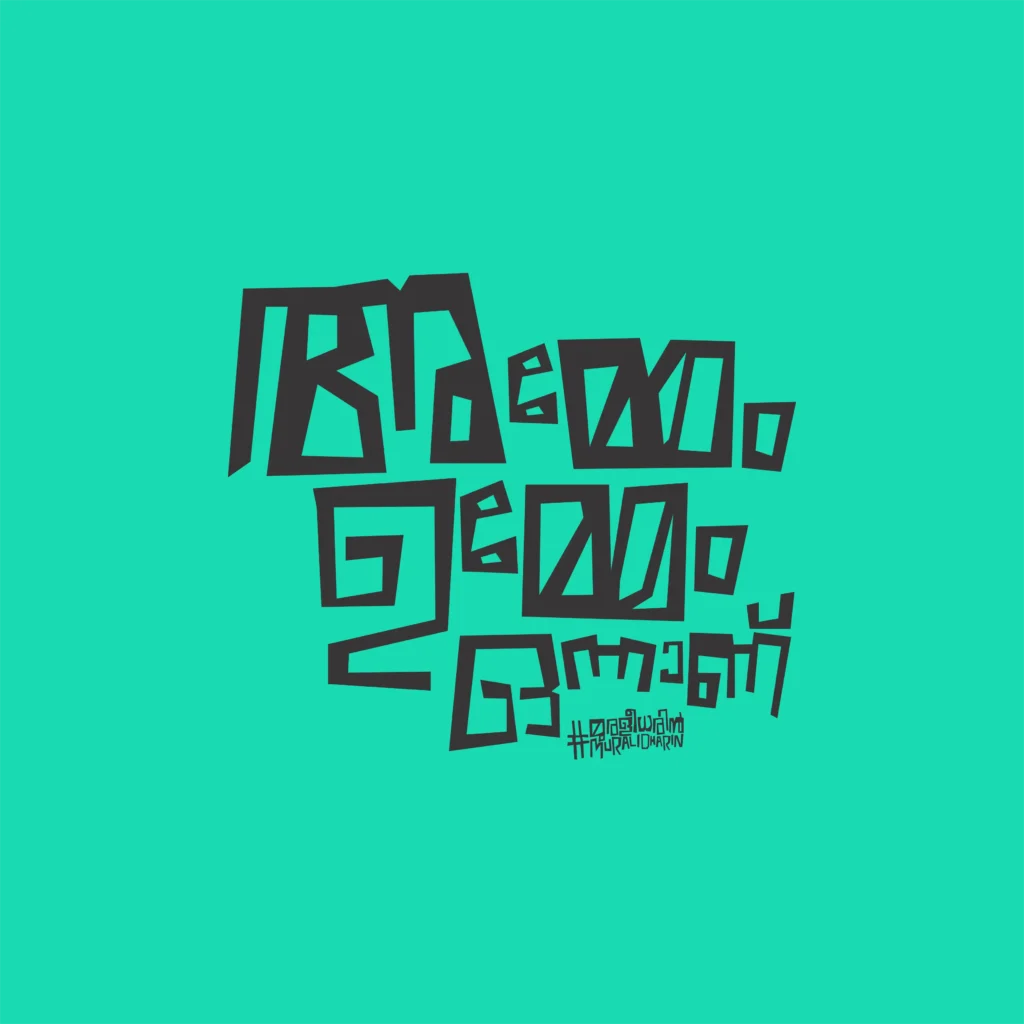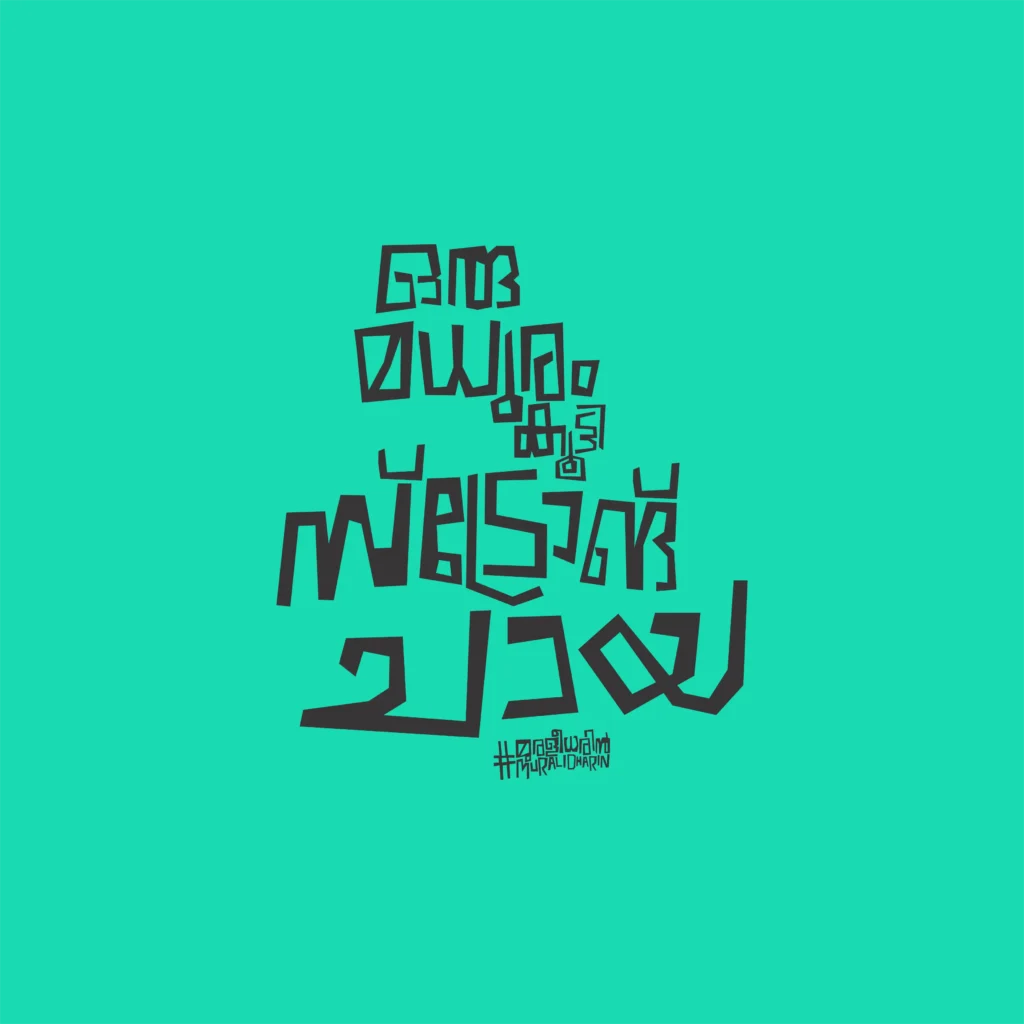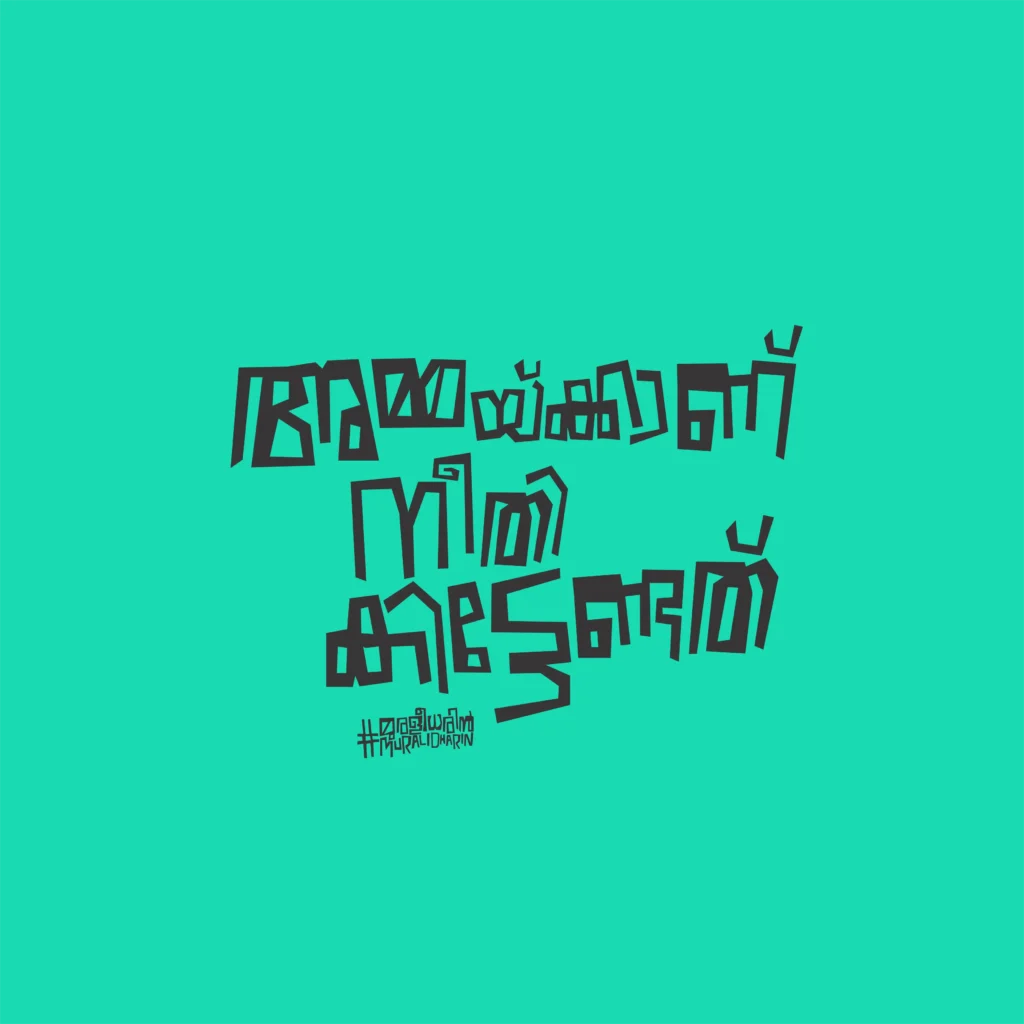
മലയാളത്തിലെ വ്യത്യസ്തമായ ഫോണ്ടുകളെ പരിചയപ്പെടുത്തുന്ന എപ്പിസോഡിലേക്ക് സ്വാഗതം. ഇന്ന് ഞാൻ നിങ്ങളെ പരിചയപ്പെടുത്തുന്ന ഒരു ഫോണ്ടിന്റെ പേരാണ് ‘അമ്മ”. വ്യത്യസ്തമായ ഒരു ഡിസൈനിൽ ക്രിയേറ്റ് ചെയ്തിരിക്കുന്ന ഫോണ്ട് ആണ് ‘അമ്മ.
ഈ ഫോണ്ട് ഡിസൈൻ ചെയ്തിരിക്കുന്നത് മുരളീധരിൻ എന്ന ഡിസൈനർ ആണ്. കുറച്ചു കാലം മുന്നേ റിലീസ് ആയിട്ടുള്ളതാണ് ഈ ഫോണ്ട്. എന്നാലും ഇതിനെക്കുറിച്ച് അറിഞ്ഞുകൂടാത്തവർക്ക് ഇത് പോസ്റ്റ് ഉപകാരപ്പെടും.
ഒരു square-rectangle ഷേപ്പിൽ ഈ ഫോണ്ട് ഡിസൈൻ വന്നിരിക്കുന്നത് . അതുകൊണ്ടുതന്നെ മലയാളത്തിൽ ഇതുവരെ കണ്ടിട്ടില്ലാത്ത ഒരു തരം ഡിസൈൻ ആണ് ‘അമ്മ ഫോണ്ടിനുള്ളത് . നിങ്ങൾക്ക് ഈ ഫോണ്ട് താഴെ കൊടുത്തിരിക്കുന്ന ലിങ്കിൽ നിന്നും ഡൗൺലോഡ് ചെയ്യാവുന്നതാണ്.
Amma is a square-rectangle typeface that can be used in various ways to amplify your projects. It is an FML font